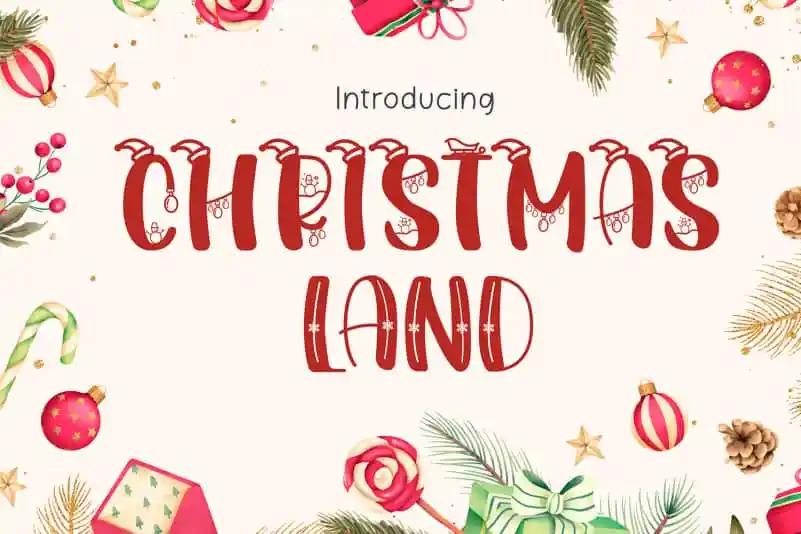
Christmasland Display Font – Download Grátis
Christmasland Display Font é uma fonte exuberante que transborda de luzes natalinas e festa, perfeita para criar mensagens animadas e visualmente atraentes durante as celebrações do Natal. Esta fonte, criada pela Lettercorner Studio, traz à tona o espírito das festas com uma tipografia colorida e vibrante que se adapta perfeitamente aos logotipos de lojas natalinas, cartões postais de fim de ano ou até mesmo às mensagens de Natal no e-mail. Suave mas agitada, esta fonte é a escolha ideal para aqueles que buscam uma maneira criativa de destacar seus projetos durante o período das celebrações, oferecendo um toque especial e personalizado que transmite instantaneamente a essência do Natal ao seu público.
Designer: Lettercorner Studio